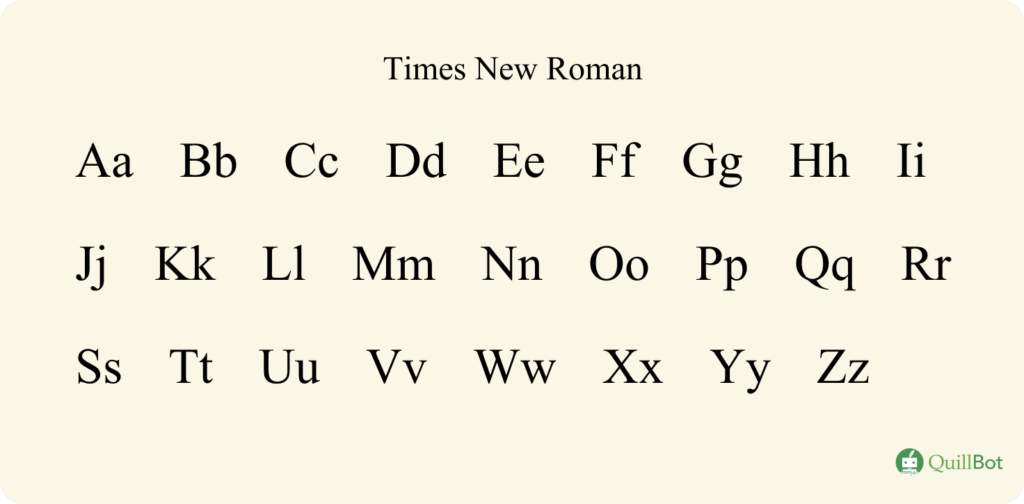
Times New Roman | Usos e história
Quando pensamos em fonte, alguns nomes vêm imediatamente à mente, por exemplo: Arial, Comic Sans MS, Helvetica, Tahoma e Times New Roman.
- Ano de criação: 1931
- País de origem: Inglaterra
- Criadores: Stanley Morison e Victor Lardent
- Comercialização: Monotype Corporation
- Tipo de fonte: Clássica, histórica
- Classificação Vox-Atypi: Real
- Popularidade: +++ (usado principalmente para publicação de livros)
- Imagem transmitida: clássica, profissional, tradicional, formal.
- Destaque especial: comunicações oficiais e documentos.
Criada originalmente para a imprensa, ela se popularizou entre o público a partir da década de 1990, graças à sua integração no Windows, em particular, como fonte padrão do Word.
A popularidade da Times New Roman também se deve à menor quantidade de papel que consome na impressão.
História da Times New Roman
Em 1929, o jornal britânico The Times, desejando mudar sua fonte para modernizar sua imagem, aumentar a legibilidade e economizar nos custos de impressão, contratou Stanley Morison, consultor da Monotype Corporation, para o trabalho.
O curioso é que o próprio Stanley Morison se tornou tipógrafo por causa de um artigo da revista Times sobre o mundo da impressão.
Com a ajuda do ilustrador Victor Lardent, Morison criou uma tipografia que otimizava o espaço impresso como nenhuma outra, permitindo ao mesmo tempo uma considerável economia de tinta.
A Times New Roman foi parcialmente baseada em duas fontes que já existiam, a Plantin e a Perpetua e ostentava uma aparência marcante e séria, mas não formal demais.
Ela foi apresentada ao público pela primeira vez em 3 de outubro de 1932.
Este é o dia em que o jornal The Times lançou sua primeira edição impressa em Times New Roman, uma fonte tipográfica criada especialmente a pedido da direção do jornal.
Foi somente no final de 1933, um ano após sua primeira aparição no jornal The Times, que seu projeto foi publicado para venda comercial ao público.
A tipografia Times New Roman passou por uma reformulação histórica em 2006, novamente encomendada pelo jornal que havia criado sua versão original.
As proporções e os detalhes mudaram ligeiramente, mas não o suficiente para serem imediatamente perceptíveis a um olhar destreinado.
O Google, que é conhecido por essas surpresinhas que fazem parte do seu charme, chama isso de easter eggs, literalmente “ovos de Páscoa”.
Esses recursos chamam-se easter eggs, porque seguem a tradição da caça aos ovos de Páscoa, e foram usados como uma metáfora pelos programadores de softwares e jogos.
Características da Times New Roman
Times New Roman é certamente a mais conhecida das fontes serifadas.
Times New Roman é de fato uma fonte serifada, ou seja, um tipo de letra com serifas. Esse tipo de fonte se diferencia das fontes sem serifa.
- As fontes serifadas possuem pequenos “pés”, ganchos ou traços decorativos nas extremidades dos caracteres. Elas evocam imediatamente um design clássico e sério, conferindo à comunicação um caráter institucional e simbolizando certa autoridade. Também são amplamente utilizadas em editoras e mídias impressas, pois são consideradas mais adequadas para a leitura de textos por períodos prolongados. Exemplos de fontes serifadas incluem: Baskerville, Garamond e Palatino Linotype.
- Por outro lado, as fontes sem serifa não possuem serifas. Suas linhas são retas e limpas. Elas têm uma aparência moderna e minimalista; seu design é limpo, porém acessível. São frequentemente usadas na web devido à sua legibilidade otimizada para telas e ao seu impacto visual. Exemplos de fontes sem serifa incluem: Arial, Aptos, Calibri, Comic Sans MS, Helvetica, Open Sans, Roboto e Tahoma.
Variações dessa fonte incluem Times New Roman Bold, Times New Roman Itálico, Times New Roman Condensed e Times Modern.
As vantagens de usar a Times New Roman são inúmeras e estão diretamente relacionadas à sua criação:
- Ela ocupa um espaço mínimo em comparação com a maioria das fontes, permitindo mais texto na mesma página/no mesmo local.
- É e continua sendo muito legível em letras pequenas, inclusive em fontes de tamanho 10 ou menores.
- É econômica no uso de tinta e, portanto, reduz os custos de impressão.
Sua reputação também é um elemento importante para o seu sucesso.
A fonte Times New Roman está associada no imaginário coletivo a uma imagem séria e tradicional, além de transmitir uma certa autoridade.
Ao ler um texto em Times New Roman, espera-se encontrar uma comunicação oficial, um artigo de imprensa de grande repercussão ou uma obra literária de qualidade.
Por outro lado, quando a Times New Roman é usada em informações triviais ou informações cuja veracidade não foi comprovada, um artigo de jornal em tom leve ou um romance de baixa qualidade, a decepção é inevitável.
Atualmente, tipografia refere-se à arte ou técnica de organizar textos e letras de maneira clara e agradável.
- Qual é a diferença entre tipografia e fonte?
Tipografia é o conceito geral de escolhas visuais envolvendo letras e textos.
Fonte é um tipo específico de letra, em geral, um arquivo digital.